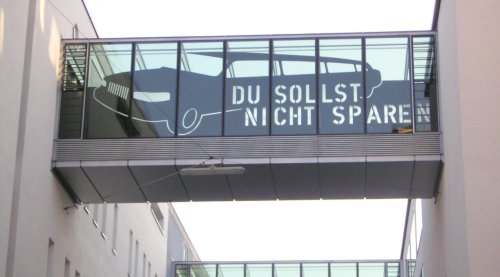
Schrift Kammerspiele München und Moma Berlin
Hier zwei Klassiker-Typo-Fragen
Moma Berlin
Den Kammerspiele-München Font sieht man in letzter Zeit ja immer mehr. 960_57617525_fbb28ff093_o_1.jpg
wer weiß bescheid?
ja, da haben sie die 'kollegen' von meta voll ins zeug gelegt
und alles aus dem suitcase herausgeholt. :roll:
»franklin gothic«:
der stencil font ist die »din schablonierschrift«
ich hatte eigentlich gedacht das moma logo wäre ein einziger font gewesen,
aber so kann man sich den effekt ja auch nachbasteln...